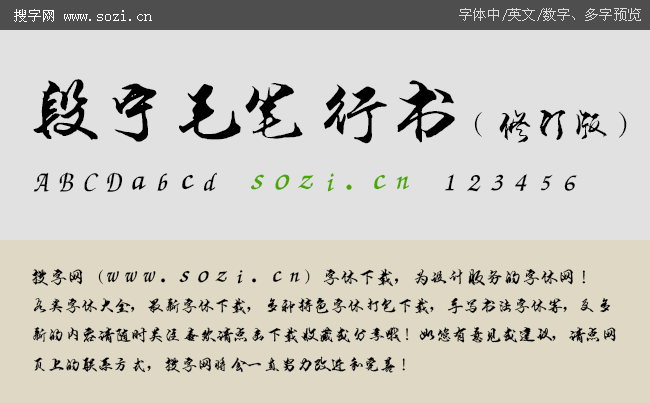
段寧毛筆行書(shū)修訂版
搜字網(wǎng)提供一款段寧毛筆行書(shū)修訂版中文書(shū)法字體下載,段寧毛筆行書(shū)修訂版是一款手定風(fēng)格的毛筆書(shū)法字體,該字體外形非常美觀,充滿(mǎn)了流線感,但結(jié)構(gòu)清晰,風(fēng)格統(tǒng)一,適合應(yīng)用于廣告設(shè)計(jì)、名片設(shè)計(jì)、包裝印刷、兒童產(chǎn)品設(shè)計(jì)等應(yīng)用。